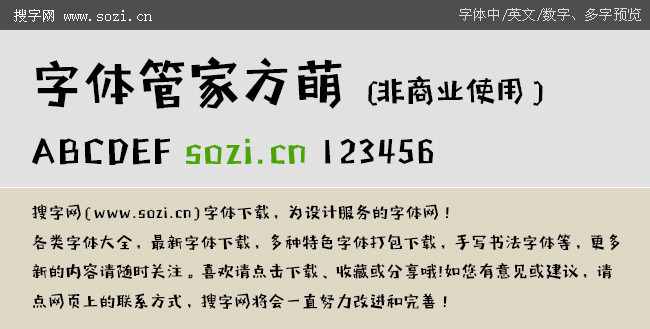
字體管家方萌(非商業(yè)使用)
搜字網(wǎng)給大家提供一字體管家方萌(非商業(yè)使用)中文字體下載,該字體是一款卡通POP字體載,字體富有變化載,字形充滿童趣載,整體散漫隨意載,識(shí)別度非常高載。適合包裝畫冊(cè)等兒童卡通宣傳廣告等應(yīng)用(此字體為個(gè)人非商用版,商用可以聯(lián)系QQ:1006760504)。